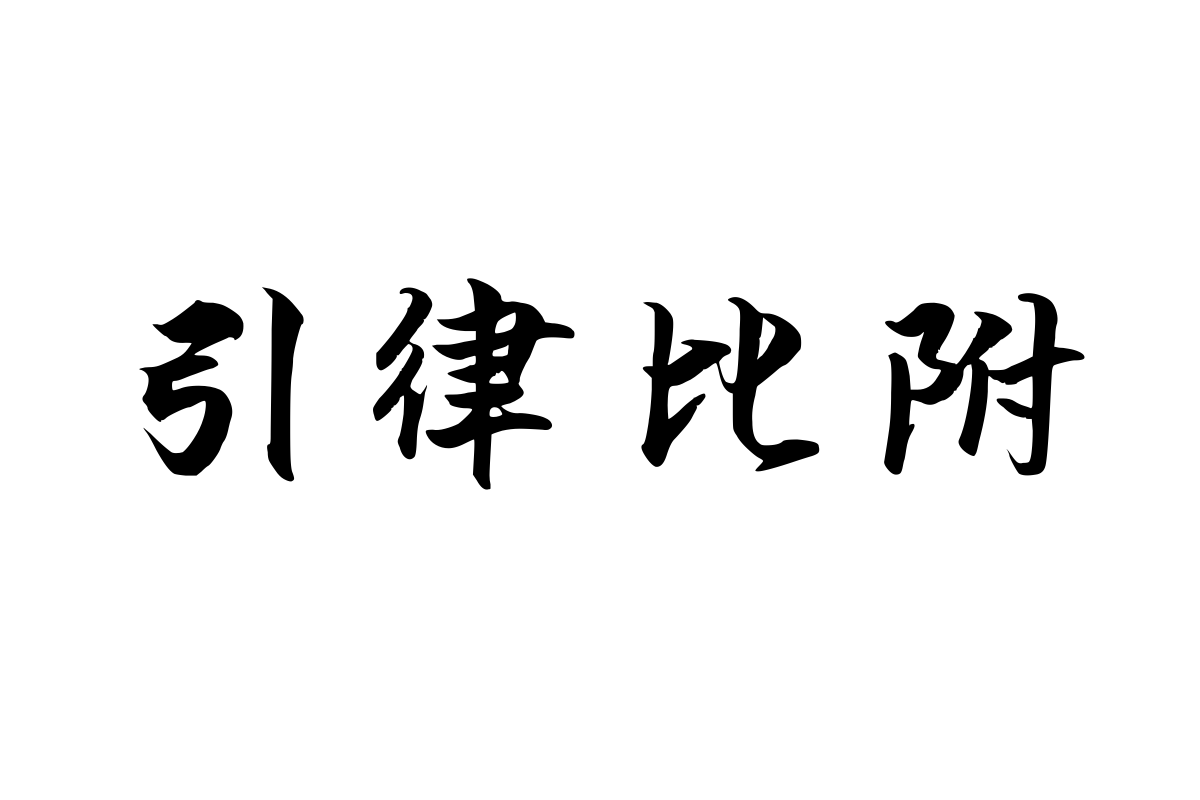
汉呈谭发社行书字体是一种书法字体,具有独特的风格和特点。以下是对该字体的一些介绍:
1. 字形结构:汉呈谭发社行书字体的字形结构较为独特,笔画粗细不一,线条流畅自然。每个字的笔画都经过精心设计,形成了一种独特的美感。
2. 笔划特征:该字体的笔划特征明显,线条粗细变化较大,既有粗犷豪放的感觉,又有细腻柔和的韵味。这种对比鲜明的笔划特征使得字体更加生动有趣。
3. 字体风格:汉呈谭发社行书字体的字体风格独特,既有传统的韵味,又不失现代感。它既适合用于正式的商务场合,也适合用于休闲的娱乐场所,具有较高的实用价值。
4. 适用范围:该字体适用于各种类型的文本,如标题、正文、广告等。无论是在报纸、杂志、书籍还是网页上,都能展现出其独特的魅力。
总之,汉呈谭发社行书字体是一种独具特色的书法字体,具有很高的艺术价值和实用性。